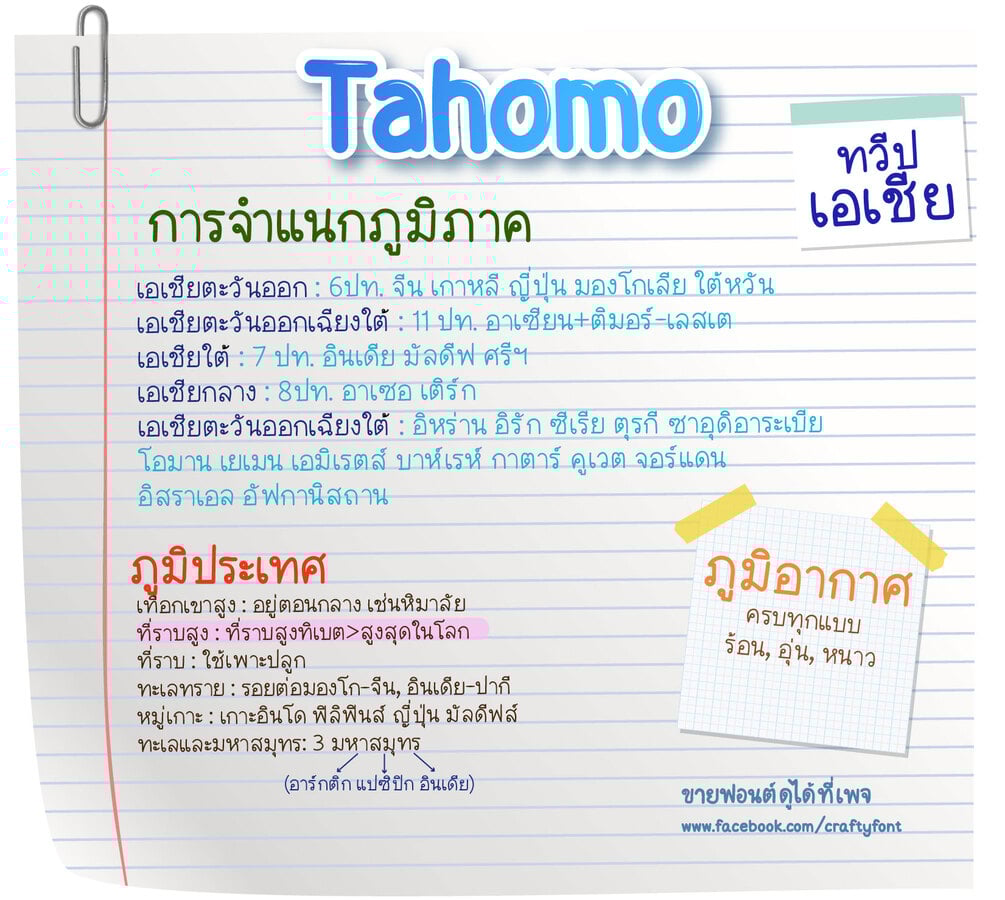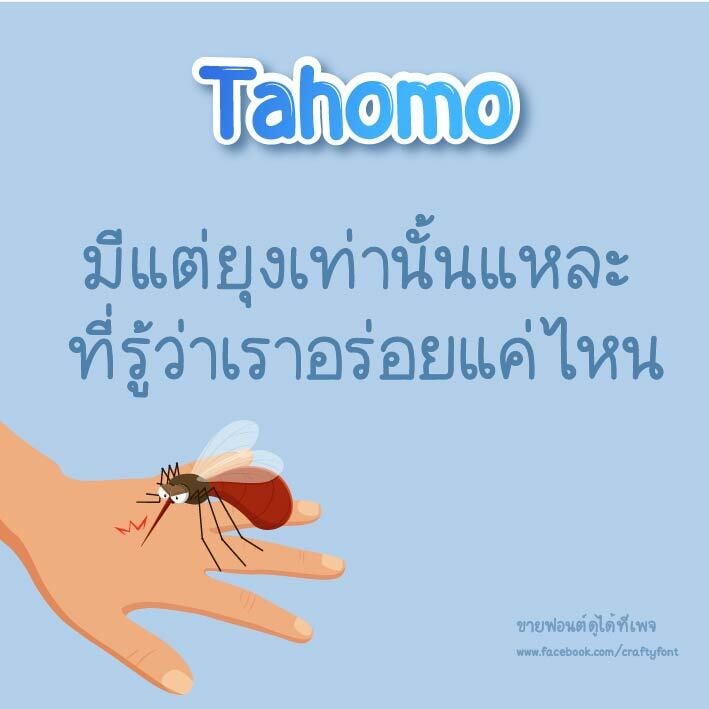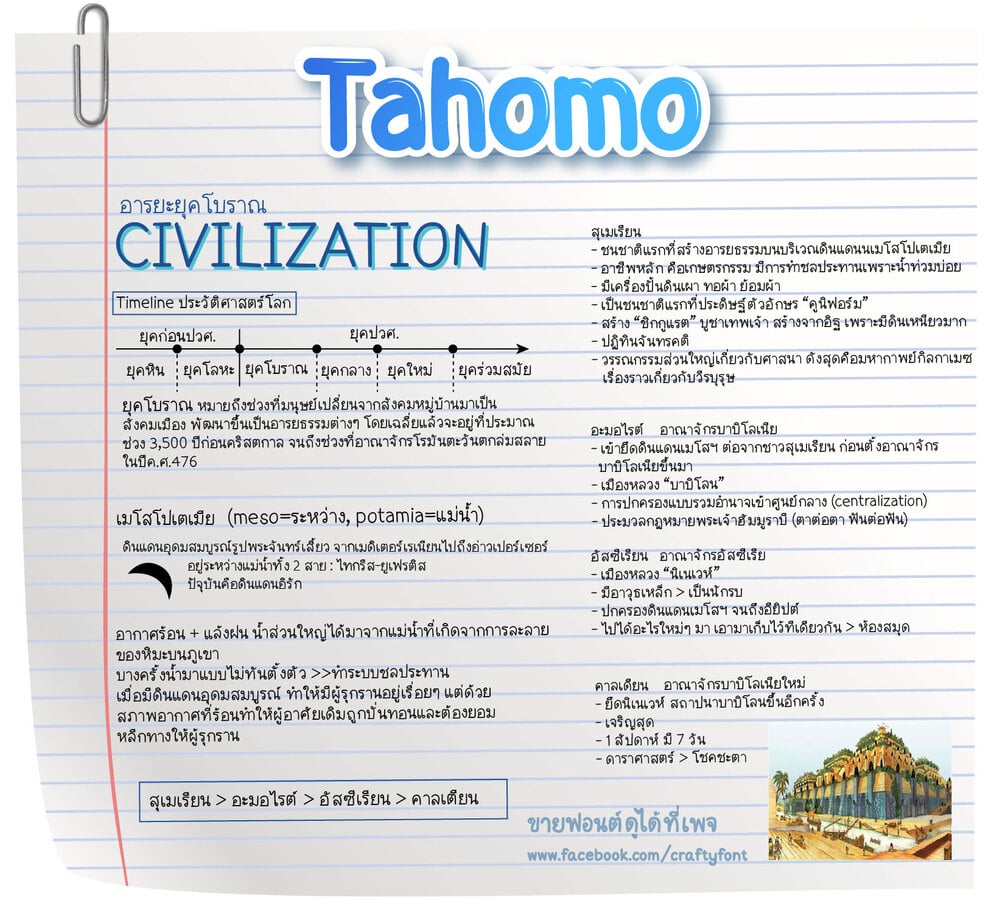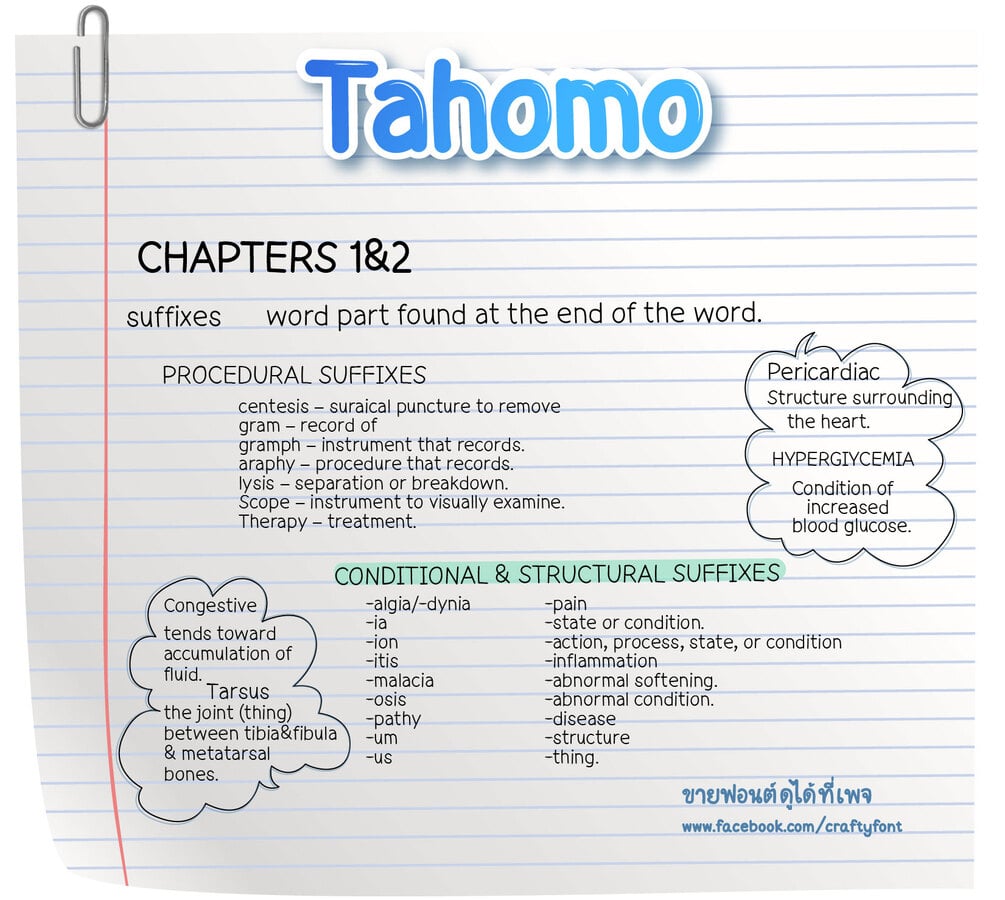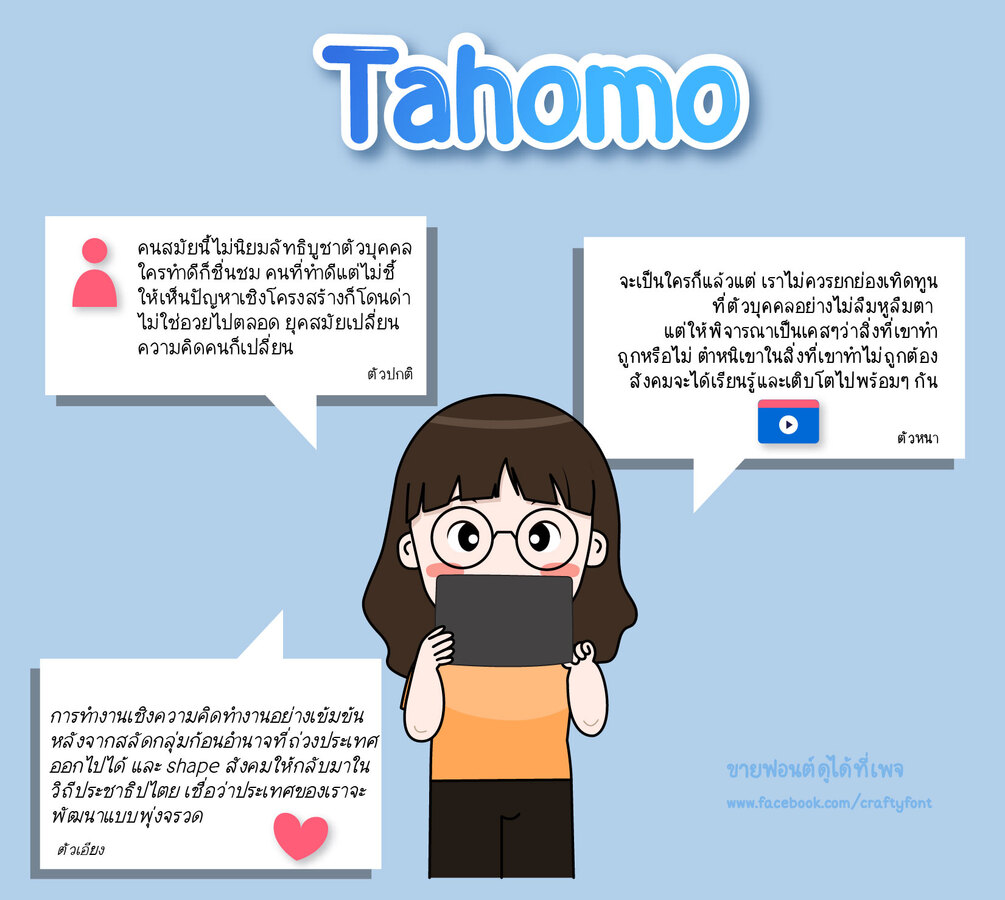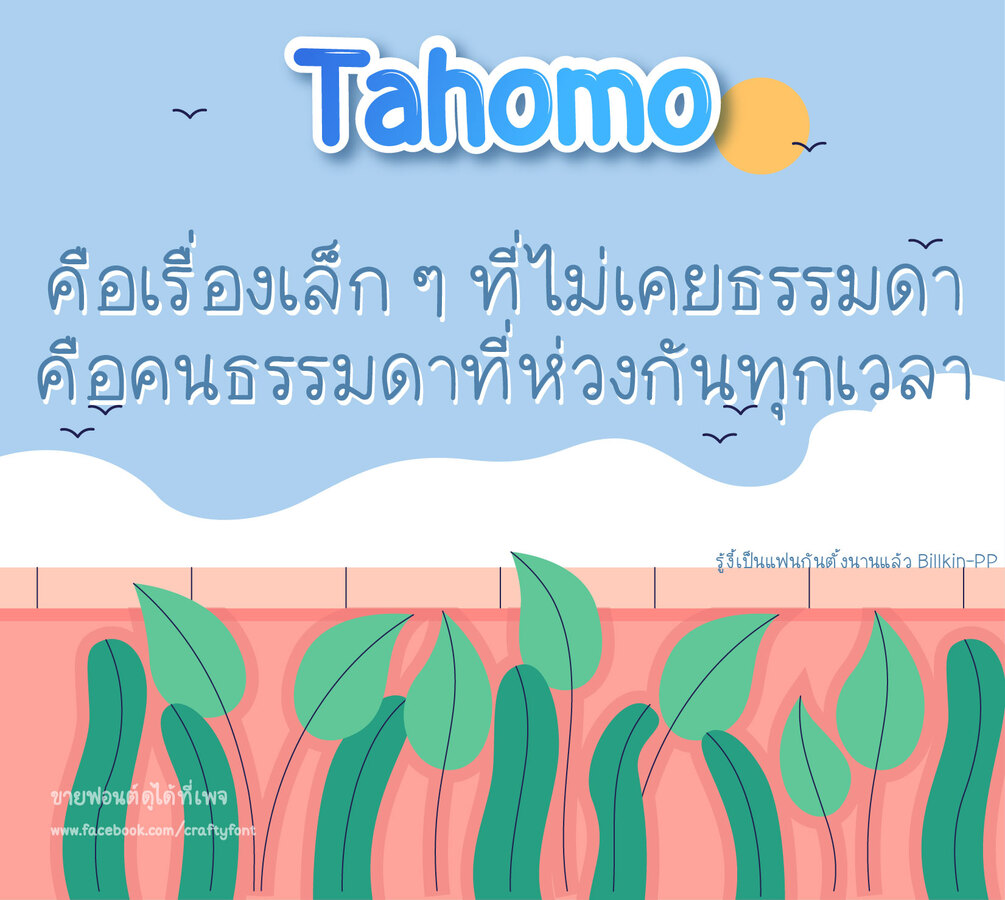
Tahomo Font (ฟอนต์ทาโฮโมะ)
ฟอนต์นี้ได้แรงบันดาลใจมาจากฟอนต์ Tahoma ฟอนต์ default ประจำเครื่อง
โดยล้อชื่อเป็น Tahomo (ทาโฮโมะ) โดยอยากให้ฟอนต์มีความทางการ แต่เขียนให้มีลายเส้นที่นุบนิบมุบมิบมากยิ่งขึ้น
ตัวใหญ่ มีระยะเยอะๆ เหมาะกับการเอาไปจดเลคเชอร์ไว้อ่านทบทวนบทเรียน อ่านสบายตามากขึ้นค่า ^^!
ใช้ได้ทั้งภาษาไทยและภาษาอังกฤษเลยน้าค้า 🥰🥰